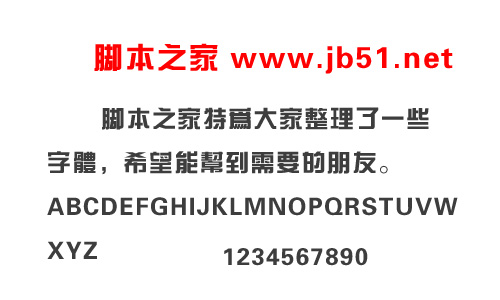
方正綜藝繁體字體是方正字體庫中的一種字體,方正綜藝是一款非常經(jīng)典的創(chuàng)意字體,從雜志報紙到街頭霓虹燈招牌都能看到它的身影。這款字體具有明顯的幾何感,字形輪廓幾乎貼近整個字面框,中宮寬松,結(jié)構(gòu)飽滿,重心平穩(wěn);筆畫較粗,粗細(xì)均勻,撇、捺筆畫呈鏡像對稱,拐彎處較為圓潤。方正綜藝的個性簡潔大方,適用于雜志標(biāo)題、品牌廣告和產(chǎn)品包裝設(shè)計。喜歡的朋友們可以前來下載使用。